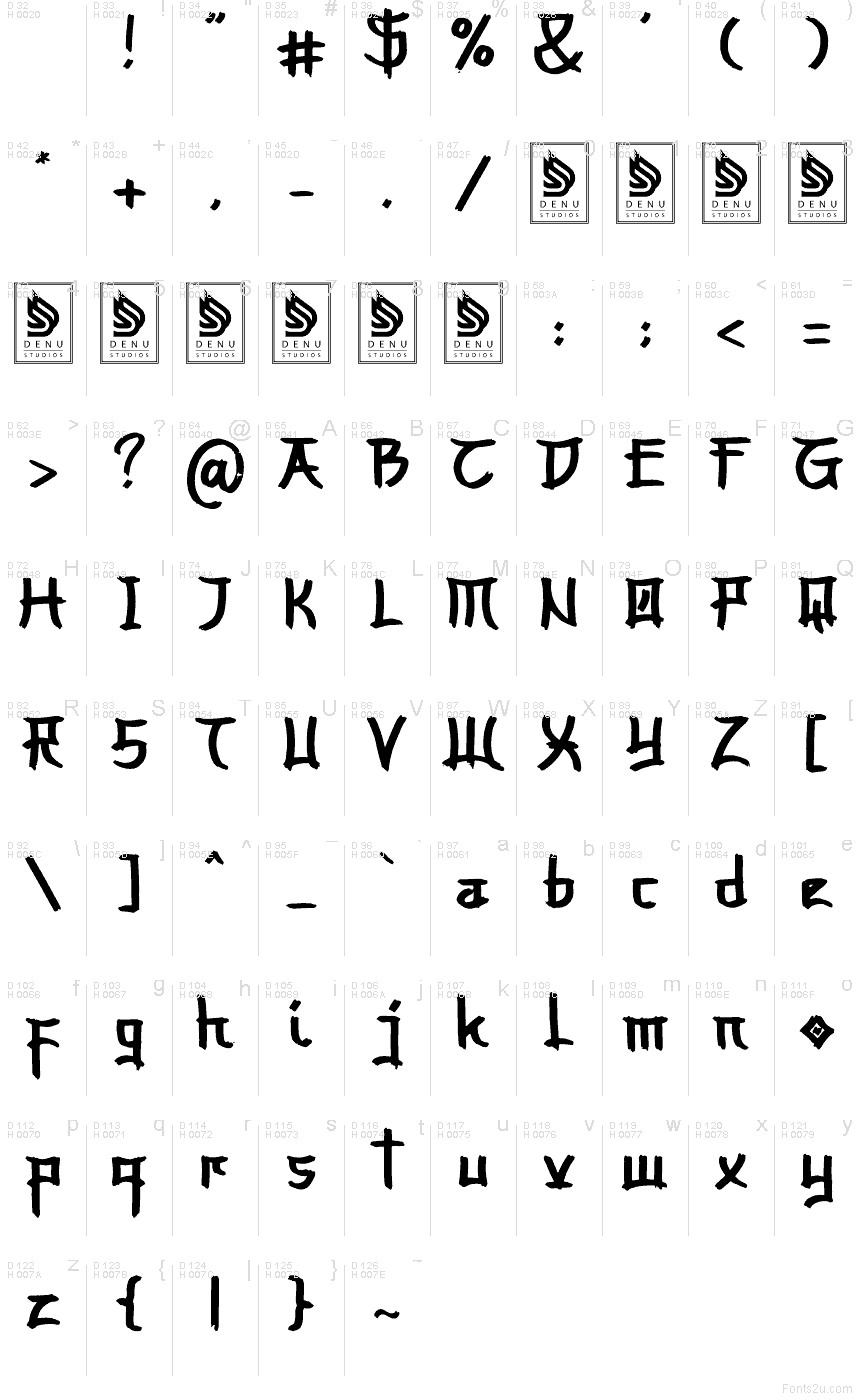
Soryu Maiden de Denustudios es una tipografía de estilo pincel japonés gratuita con una presencia cruda y cargada de tinta. Las letras parecen cortadas de un rápido trazo caligráfico, con trazos gruesos, bordes irregulares y un ritmo dibujado a mano que resulta más folclórico que pulido; incluso la "o" en forma de diamante refuerza ese aire emblemático, como de letrero de santuario.
Encaja a la perfección en títulos de carteles, logotipos de videojuegos, portadas inspiradas en el manga, identidad de restaurantes y gráficos de eventos donde una fuente gratuita necesite un toque cultural audaz sin volverse demasiado refinada. Dado que las formas se sienten pintadas en lugar de diseñadas digitalmente, también funciona muy bien para titulares cortos, carteles de títulos y monogramas que necesiten un poco de dramatismo ritual y un toque artesanal.